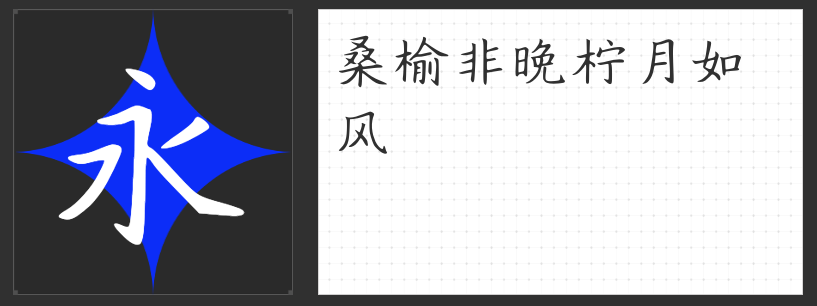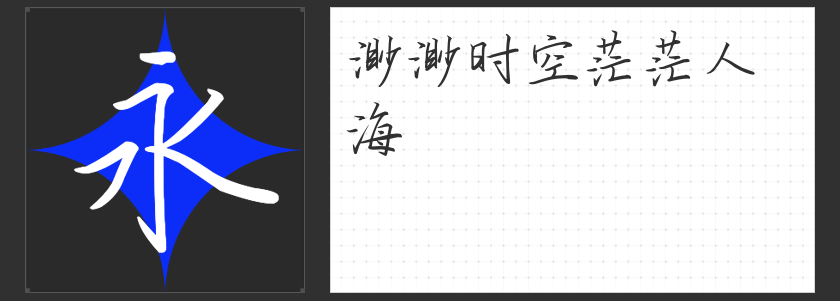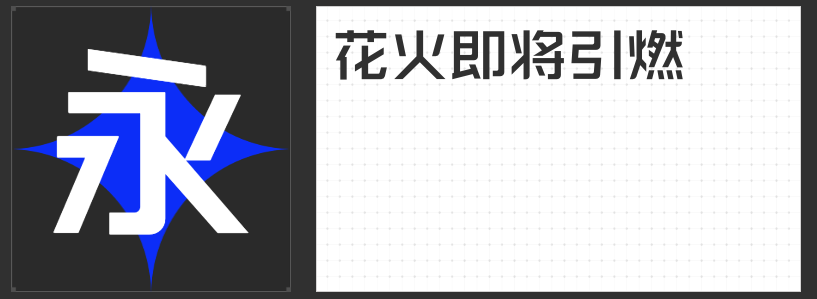
笔墨凝香:四款经典字体唤醒怀旧设计的时间美学
在怀旧主题的设计语境中,字体不仅是信息载体,更是时光的容器。它们以独特的笔触与结构,将记忆中的温度、质感与情绪凝练成视觉符号。以下四款字体,或刚劲或柔美,或古朴或灵动,以多元风格为怀旧设计注入跨越时空的叙事力量。
一、励字勇敢黑简 中黑
这款无衬线手写字体以粗壮笔划构建视觉张力,撇捺收笔处采用钝角处理,摒弃尖锐锋芒,转而以浑圆形态传递沉稳质感。横竖笔画的均匀分布与适度留白,既保证了远距离阅读的清晰度,又通过笔触的粗细变化暗藏书写者的力度节奏。其醒目而不失内敛的气质,仿佛旧时工厂的金属铭牌或老式招牌,以简洁有力的视觉语言承载集体记忆的厚重感,尤其适合作为怀旧主题的标题或标志字体。
二、云书法三行魏碑体
取法魏碑精髓的楷书字体,将碑刻的苍劲与手写的灵动融为一体。笔划起收处保留方峻棱角,中段却以流畅弧线软化刚硬气质,形成“朴拙险峻,舒畅流丽”的独特张力。字型结构在工整中见变化,如旧时牌匾上的书法,既符合传统审美框架,又通过笔触的细微颤动展现手工书写的温度。这款字体适用于需要营造历史厚重感的标题或正文,让文字仿佛从泛黄古籍中自然生长而出。
三、励字行草简繁
介于行书与草书之间的过渡书体,以简化的草法结构提升辨识度,同时保留行书的连贯韵律。字体线条如旧信笺上的墨迹,随情绪起伏自然轻重,笔断意连处暗藏书写节奏。其动态平衡的视觉效果,既避免了草书的难以辨识,又突破了行书的刻板,适合需要表达时间流动感的怀旧文案或装饰性元素,让文字成为承载记忆的流动媒介。
四、云书法惠中行书体
这款行书字体以楷书的端庄为基底,融入草书的洒脱连笔,形成“雍容大气而不失灵动”的独特气质。笔划间的牵丝映带如旧时文人书信的自然流露,字面工整却因微妙的倾斜角度打破呆板,整体呈现柔和舒展的视觉感受。其克制而不失个性的表达,适合需要传递温暖记忆的怀旧主题正文或短标题,让文字在清晰可读中透出岁月沉淀的优雅。
四款字体,四种书写记忆的打开方式。它们以笔墨为舟,载着观者穿越时空,在怀旧设计的语境中,重拾那些被遗忘的温柔与力量。